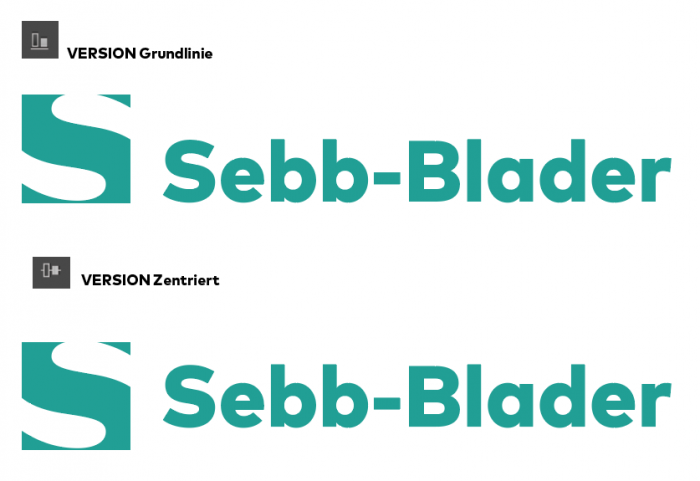
Ausrichtung der Bildmarke an der Wortmarke
welche Anordnung empfehlt ihr mir?
Der Vorteil von Version Grundlinie ist jener, dass ich Bild- und Wortmarke auf einer Grundlinie habe und so eine schöne Kante zum positionieren habe. In kleinen Anwendungen ist das besonders praktisch, weil ich weniger Weißraum unter dem Logo benötige, sollte dort noch Text platziert werden.
Ästhetischer finde ich allerdings Version B. Wenn ich mir das Logo an einer Wand vorstelle, fände ich Logo Version B deutlich schöner oder ein weiteres Beispiel: Alleinstehend auf einer Visitenkarte.
Sollte man beide Versionen abhängig von der Anwendung zulassen, oder ist es schlauer, sich für eine Version zu entscheiden um einfacher stringent zu bleiben?
Was meint ihr?
Mir gefällt Version a besser. Es wirkt für mich etwas willkürlich, wenn die Wortmarke nicht auf der Grundlinie steht, ich sehe keinen zwingenden Bezugspunkt zur Bildmarke, wenn sie so halbhoch steht wie in der zweiten Version.
Weder noch. Das "S" ist für meine Begriffe rein zufällig beschnitten, eine Aussage, einen Sinn oder eine Absicht dahinter kann ich nicht erkennen. Daher ergibt sich für mich keine passende Anordnung.
Das "S" ist für meine Begriffe rein zufällig beschnitten, eine Aussage, einen Sinn oder eine Absicht dahinter kann ich nicht erkennen.
Ich sehe da das S auch erst beim zweiten Hinsehen.
sollte es sich bei diesem beschnippelten S vielleicht nur um einen Logo-Dummy handeln, der nur mal schnell für die Frage gebaut wurde?
Ja. Ich dachte das wäre offensichtlich, bei einem Namen wie Sebb Blader.
Nein, ich zumindest habe das wirklich ernst genommen, da ich des öftern schon solche Werke gesehen habe. Und in mindestens einem Fall hätte man das Logo, ein stilisiertes kapazitives Tastenfeld, als O in den Firmennamen ziehen können.
Zur Veranschaulichung: Das Tastenfeld sieht etwa [·] so, aber um 90° gedreht aus. Also PIC[·]SENS statt [·] PICOSENS
Jetzt hast du mich so sehr verwirrt wie ich euch. Glückwunsch :biglove:
Ah so. Ich persönlich kann anhand eines Logo-Dummys nichts beurteilen, weil sich im richtigen Logo ganz andere Proportionen und Beziehungen auftun.
Und ich finde: Logo und Text zentriert funktioniert nur dann gut, wenn sowohl das Logo als auch der Text dahinter eine deutliche vertikale Symmetrie aufweisen, also z.B. der Text im Versalsatz gesetzt ist. Bei gemischen Satz wirkt der Text, zum Logo vertikal zentriert trotzdem optisch zu tief.
Ganz generell kann man aber schon sagen, dass man es sich für später leichter machen kann, wenn man in's Logo klare Bezugspunkte/-linien einbaut, an denen man andere Objekte ausrichten kann. Denn: Ein Logo steht ja nachher nicht immer ganz alleine, sondern ist ein Teil eines ganzen Designs.
Ich habe regelmäßig mit einem Logo zu tun (es ist nicht von mir), das auch immer wieder schwer auszurichten ist. Eigentlich passt es nur oben links, aber selbst dann muss man gucken, wie man mit dem Rand und eventuellen Elementen darunter umgeht. Deswegen überlege ich solche Einsatzgebiete immer gleich mit und würde eher zu Beispiel 1 tendieren.
Generell mag die Ausrichtung an der Grundline, aber es könnte z.B. alles wieder ganz anders wirken, wenn in dem Namen Unterlängen vorkämen.
Sehr guter Punkt! Klasse! Kommt im tatsächlichen Logo nicht vor.
Selbst wenn, könnte man auch in Versalien setzen ;)
wie sieht es aus mit der ausrichtung an den oberkanten. ist vielleicht da die beste lösung.
anm: was mich nach wie vor irritiert: die wiederholung des anfangsbuchstabens in der bildmarke. das lässt sich ev. abschwächen wenn bildmarke und wortmarke versch. farben bekommen.
Ich glaube, das ist das, was Uwe oben meinte: Er würde statt der Doppelung eines Buchstabens in Wort- und Bildmarke eher versuchen, die Bildmarke in die Wortmarke zu integrieren. Richtig Uwe?
das braucht nicht zu irritieren, Bild-und Wortmarke sind nur Dummies, um die Frage deutlicher zu illustrieren.
Und ja, bei der fast unendlichen Möglichkeit, ein Logo zu gestalten, kann alles möglich sein, mal ist Oben bündig die Ideallösung, mal zentriert, mal unten und mal irgend etwas ganz anders. Generell kann man das kaum sagen
(ich meinte natürlich nach Mundstuhl-Art: „Geschatalten“ )
gesataltzen
Zum Kunden, dem Tyrannen, schlich,
Catfonts, den Stift im Gewande.
Ihn frug die Grafikerbande:
»Was wolltest Du mit dem Logo? Sprich!«*   ;-)
So ganz nebenbei bemerkt, aber doch schon leicht angesäuert, fragen sich die meisten hier sicherlich auch, warum Du hier die ganze Gruppe mit einem leicht angetäuschten, verwischten und dann gleichzeitig wieder in Frage gestellten – sagen wir: … Logo – verwirrst.
Etwas »Butter bei die Fische«, heißt es bei uns oben im Norden, oder auch:
»Komm’ zur Sache, Schätzchen!«